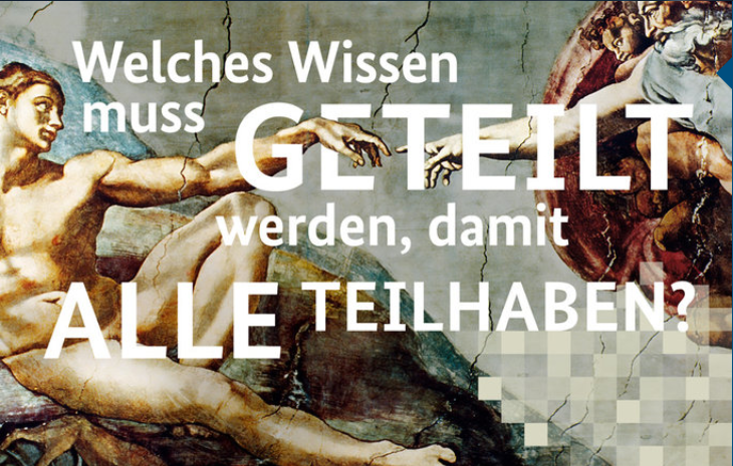
Welche Schrift ist das? (geteiltes Wissen)
Da dies Foto nur unscharf im Internet zur Verfügung steht, muss ich es selbst zusammenfriemeln ;-)
Das ist die "BundesSans", wird – auch in diesem Plakat des BMBF – von der Bundesregierung verwendet.